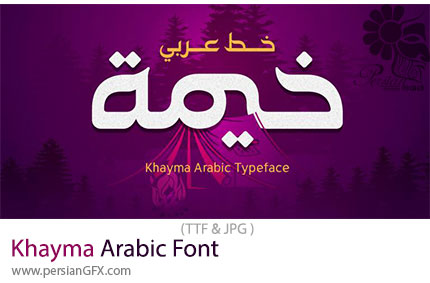
در این بخش شاهد فونت عربی خیمه می باشید که با فرمت TTF بر روی سایت برای دانلود قرار گرفته است. فونت خیمه (Khayma) یک تایپفیس زیبای عربی است که با الهام از خطوط سنتی و ترکیب آنها با استایل مدرن طراحی شده است. این فونت به دلیل طراحی خاص و هندسه منحصر به فردش، یکی از انتخابهای محبوب برای طراحیهای گرافیکی، بستهبندی، برندینگ و پروژههای دیجیتال به شمار میرود. فونت خیمه ترکیبی از اصالت خوشنویسی عربی و زیباییشناسی مدرن است که برای کاربردهای متنوع قابل استفاده است. این فونت در پروژههای چاپی، دیجیتال و تبلیغاتی به خوبی عمل میکند. فونت Khayma انتخابی استثنایی برای طراحانی است که به دنبال فونتی خاص و جذاب با تم عربی هستند. این فونت با زیبایی و انعطافپذیری خود، میتواند هر پروژهای را به سطح بالاتری از حرفهای بودن برساند.